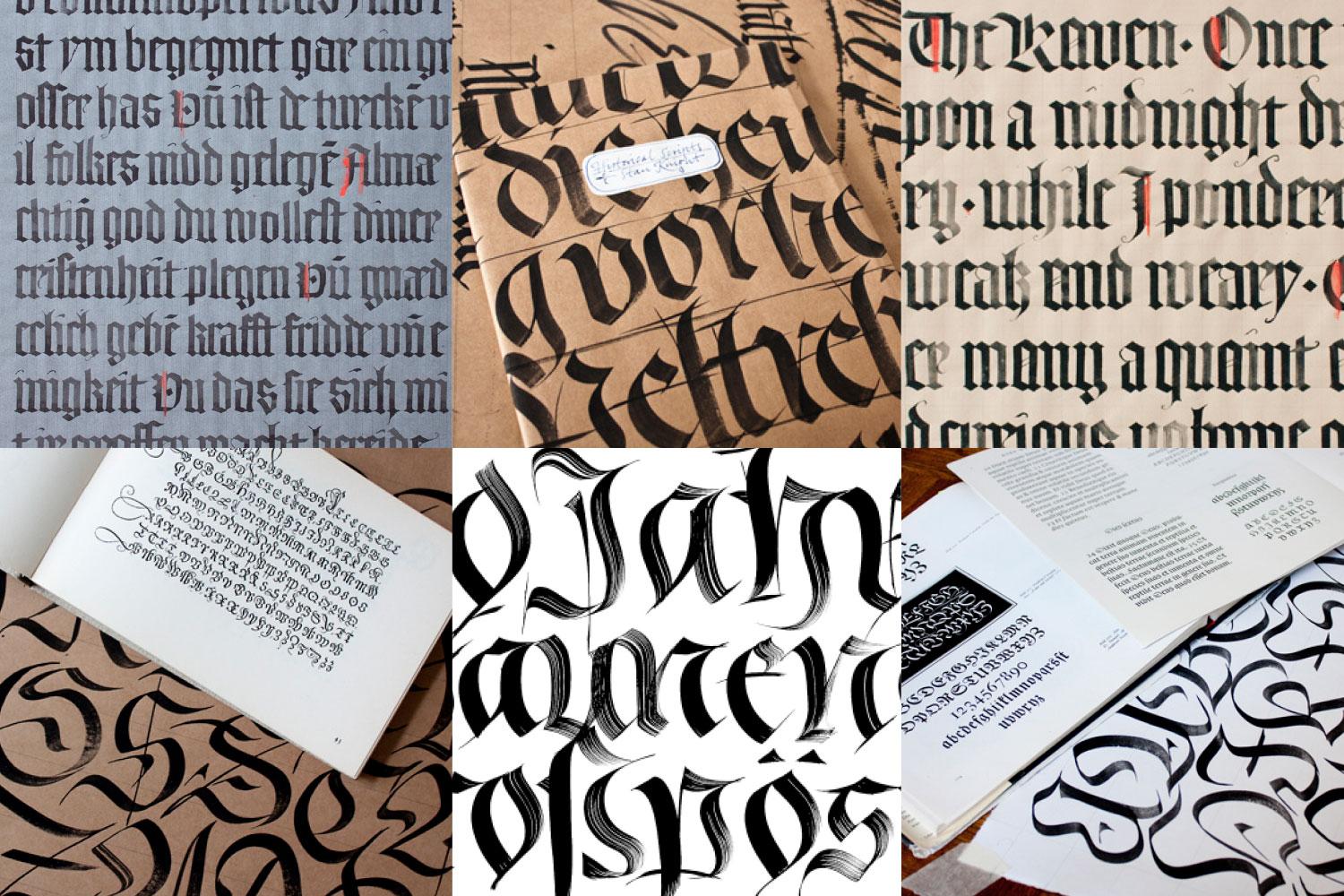
Von Textura zur Fraktur (Kalligrafie-Kurs)
Textura, Blackletter, Gothic Script und Fraktur sind alles verschiedene Bezeichnungen für Schriften, die scheinbar eher dunkel und eckig im heutigen Gebrauch von Schrift bestimmte Schubladen bedienen. Man findet sie auf den Ettiketten von Bierflaschen oder in den Logos von Metal und Hardrockbands. Auch in der Gothic-Szene und beim Tätowierer sind sie nach wie vor gefragt. Das alles lässt wenig vermuten, dass das erste mit beweglichen Lettern gedruckte Buch der westlichen Welt, Gutenbergs 42-zeilige Bibel, in einer Texturschrift gedruckt war.
Im 12. Jahrhundert entstehen in Mittel- und Nordeuropa Schriftformen in der Buchschrift, die man heute als gebrochene Schriften bezeichnet. Diese Schriftformen werden dann über die Renaissance in Europa weiterentwickelt und bleiben in Deutschland bis in die 1940iger Jahre in der Typografie die vorherrschende Schriftform. Noch im Anfang des 20. Jahrd. kamen durch Rudolf Koch, paralell zur Arts and Crafts Bewegung in England, wichtige neue Impulse für einen neuen und lebendigen Umgang mit gebrochenen Schriften in die Kalligrafie und Schriftgestaltung.
In dem Wochendworkshop mit dem Schriftgestalter Tobias-David Albert wollen wir gemeinsam ganz praktisch die Wurzeln dieser Schriftformen kennen lernen. Die Textura bildet dabei den Ausgangspunkt um kalligrafisch eine gute Orientierung in der Welt der gebrochenen Schriften zu entwickeln. Anhand von Schreibvorlagen wird mit Rohrfedern, Paralell-Pen und anderen Schreibgeräten gearbeitet. Dazu gibt es Hintergrundwissen zur Beziehung von gebrochenen Schriften zur Antiqua. Das wiederum führt auch zu einem bessseren Verständnis der Formen, der heute gebräuchlichen Buchschriften in der Typografie – oder macht einfach Spaß zu entdecken. Große, kleine, kuriose und moderne Werkzeuge, Tinten, Papier und weiterführende Literatur werden vorgestellt. Bei Interesse könnte ein aufbauender Kurs für Fraktur und Schwabacher Schrift anschließen.